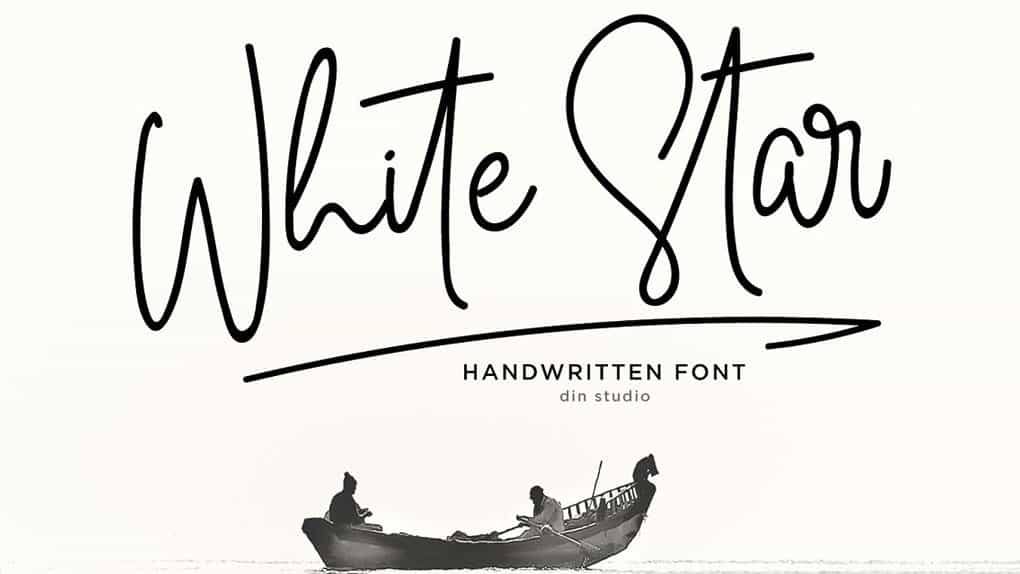
فونت انگلیسی دست نویس White Star – Chic Handwritten Font
فونت انگلیسی دست نویس White : در این پست یک فونت انگلیسی با نام White Star به شما معرفی میشود که در انواع پروژه های شما مجموعه حروف زیبا و شیک را به ارمغان می آورد. این فونت یکی از بهترین انتخاب ها برای موضوعات لوگو ، مارک تجاری ، عروسی و نقل قول است.